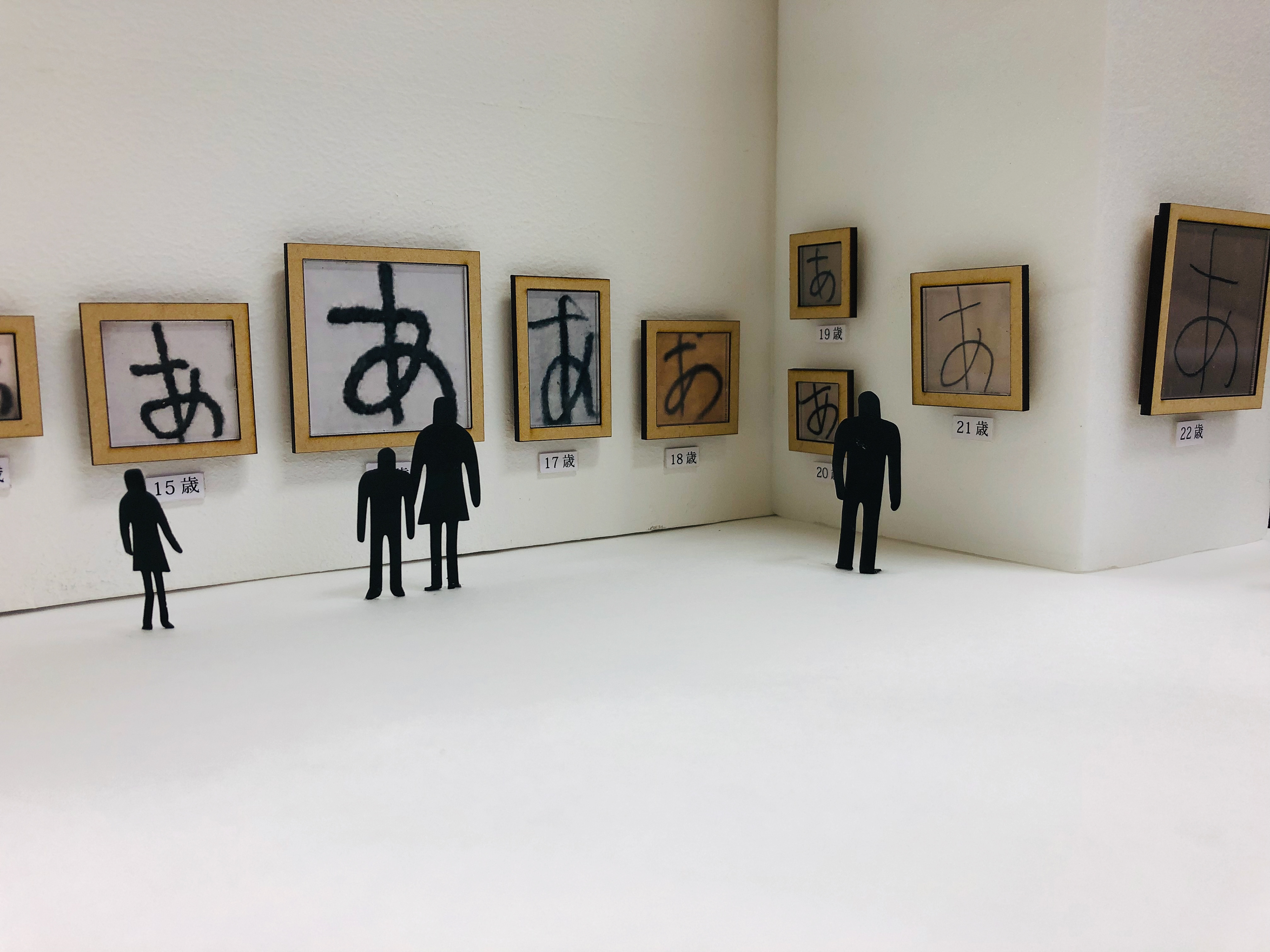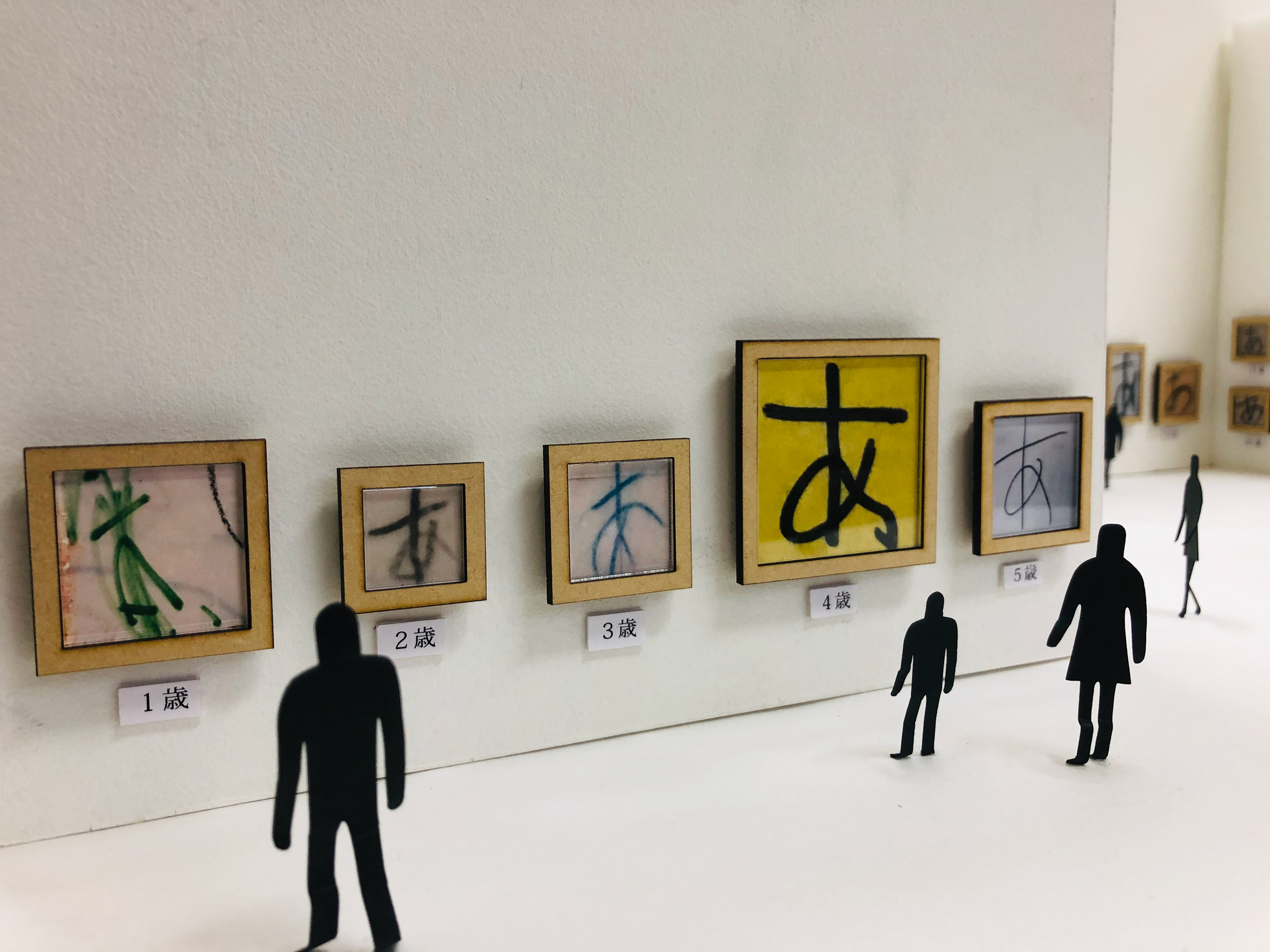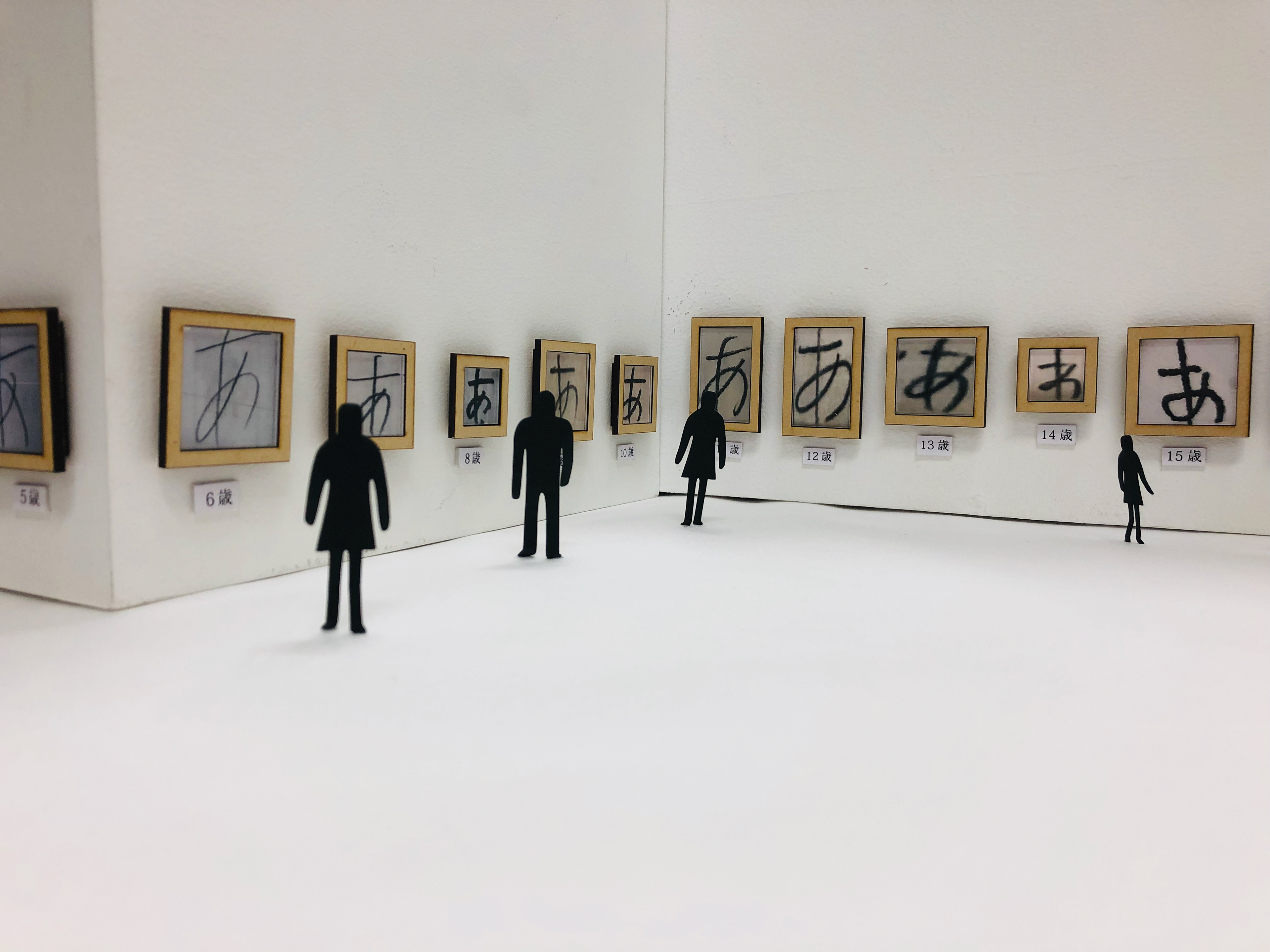
自分の筆跡展覧会
私が生まれてから22歳に至るまでの「あ」を集めて、1年ごとに額に入れ展覧会を催すと想定した妄想作品です。
concept
自分の成長や特徴を「文字」の視点から顕在化しようと試みました。幼い頃はたどたどしく、時より丸みを帯びたり、つぶれたりしています。
16歳時点の「あ」が好きです。